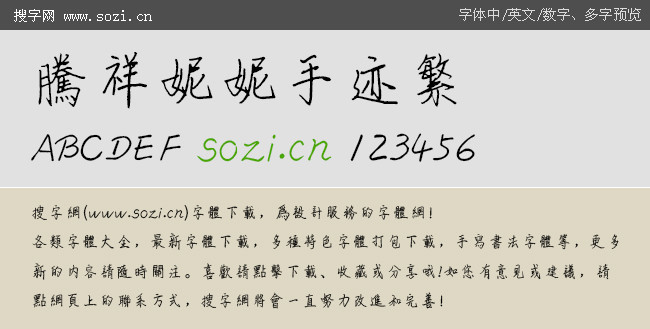
騰祥妮妮手跡繁
搜字網(wǎng)提供一款騰祥妮妮手跡繁中文藝術(shù)字體下載,騰祥妮妮手跡繁是一款很漂亮的手寫字體,書寫風(fēng)格自然流暢,獨具風(fēng)格,稚拙中透顯出活潑靈動的氣息;無雕琢,無拘束質(zhì)樸的視覺效果,用于正文更體現(xiàn)出手寫自然之感。字體可以廣泛應(yīng)用于印刷出版、包裝設(shè)計、廣告設(shè)計、網(wǎng)頁設(shè)計等領(lǐng)域。